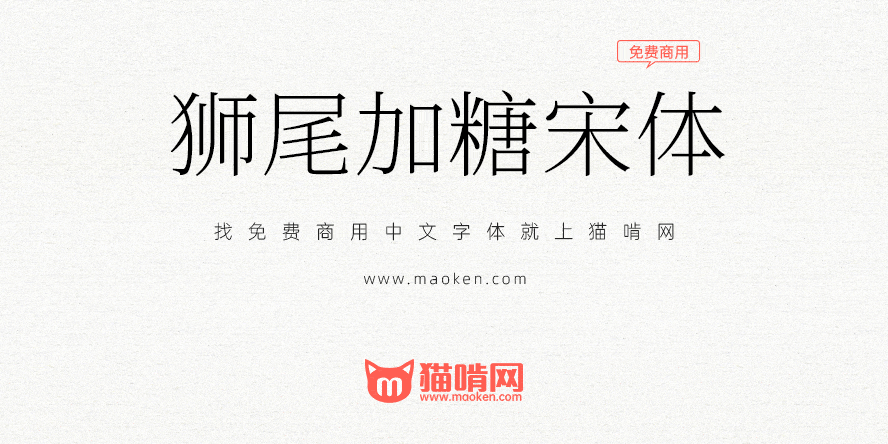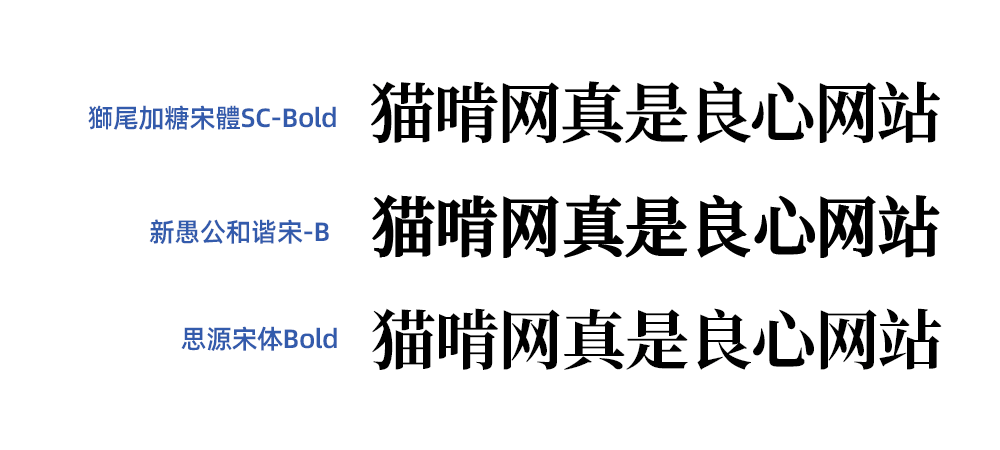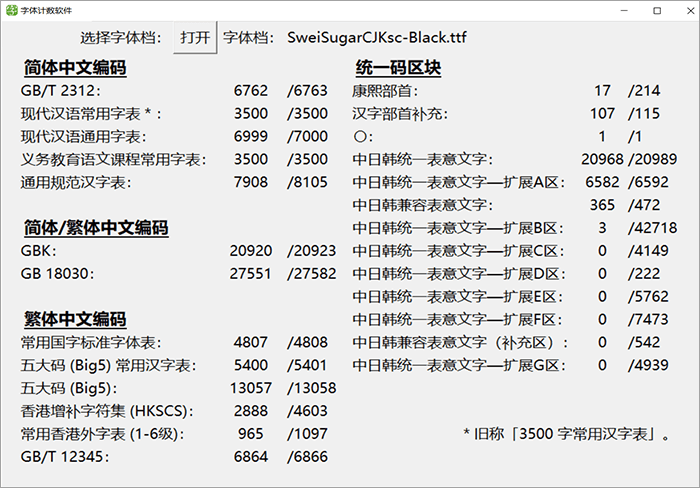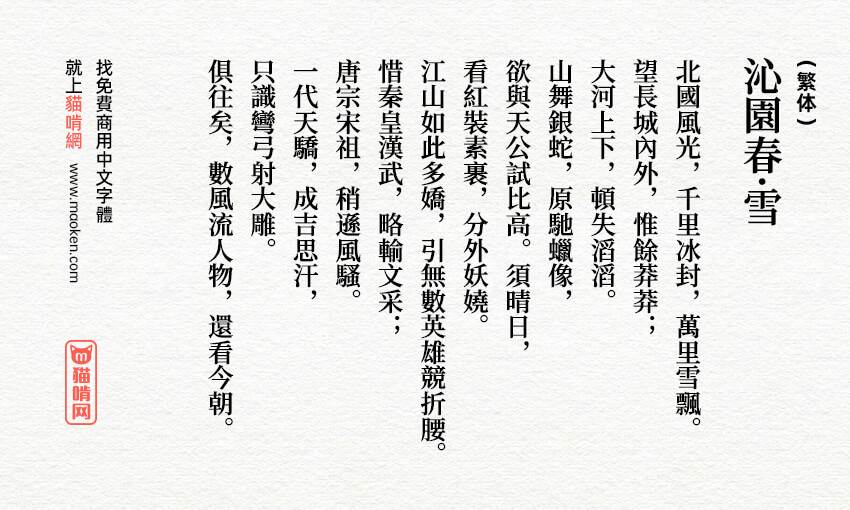
狮尾加糖宋体是台湾友人Max发布的基于思源宋体的横笔进行加粗改造字体。和思源宋体的不同之处,思源宋体的横笔较细,狮尾加糖宋体是对字体进行了加粗处理,使宋体字形看上去更和谐。
狮尾加糖宋体和@新愚公发布的新愚公和谐宋思路基本一致,但是在实际效果上略有差异。新愚公和谐宋笔画会更粗一点,而狮尾加糖宋体看上去会更精致一点。大家可以按自己的喜好进行选择下载。
这款是加粗,可以出一款减细横笔画的版本吗,很多明朝体都是比思源横比要细的,适合做标题,,横比加粗的适合正文。
SemiBold级的英文大小写O字下面不圆